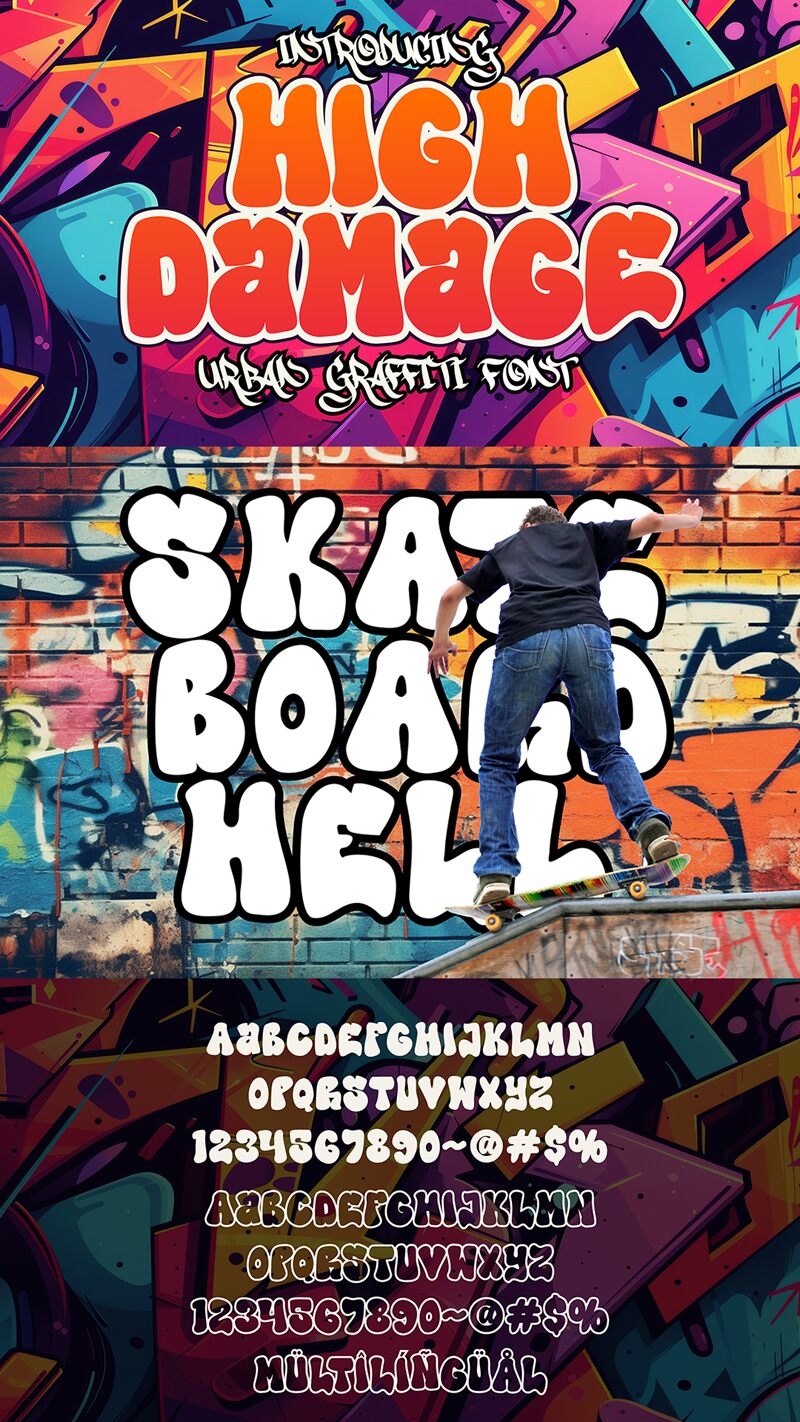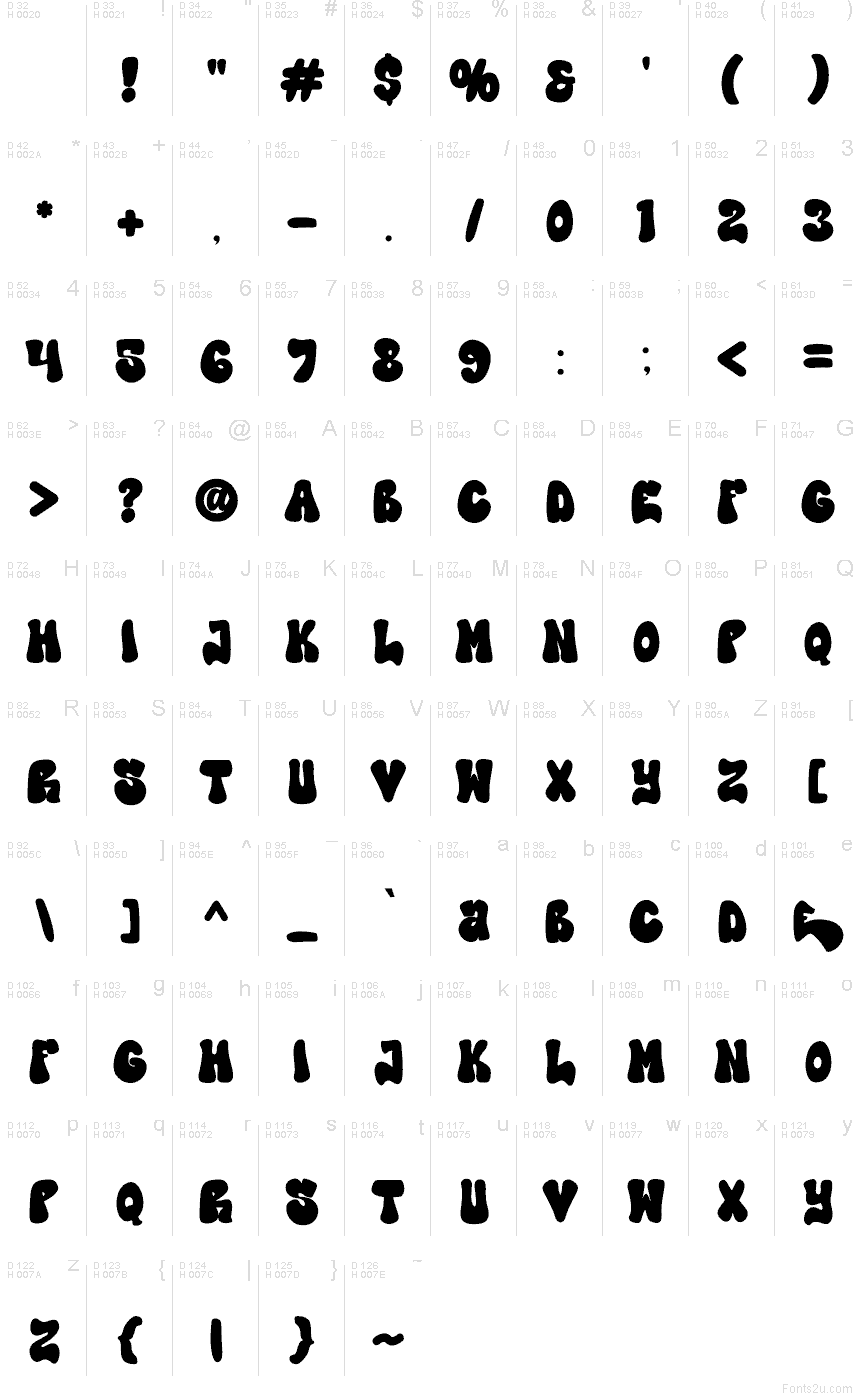
Il font High Damage di Saepul milah di CikareotypeStudio x figureeStudio è un font graffiti gratuito con macchie di inchiostro corpose che sembrano vernice fresca spinta con forza contro un muro. Le lettere si incastrano con un ritmo vivace, con angoli morbidi e colature occasionali che rendono l'intero lettering rumoroso, appiccicoso e vitale.
Utilizzare High Damage su loghi streetwear, poster da skate, copertine di album, pacchetti di adesivi, miniature di YouTube, flyer di eventi e titoli d'impatto conferisce subito un atteggiamento forte senza bisogno di effetti aggiuntivi. Impostalo in grande con un po' di spaziatura extra, quindi abbinalo a un sans serif stretto e pulito per date, prezzi o crediti: questo font gratuito ci pensa a urlare, mentre il sans serif mantiene la leggibilità.